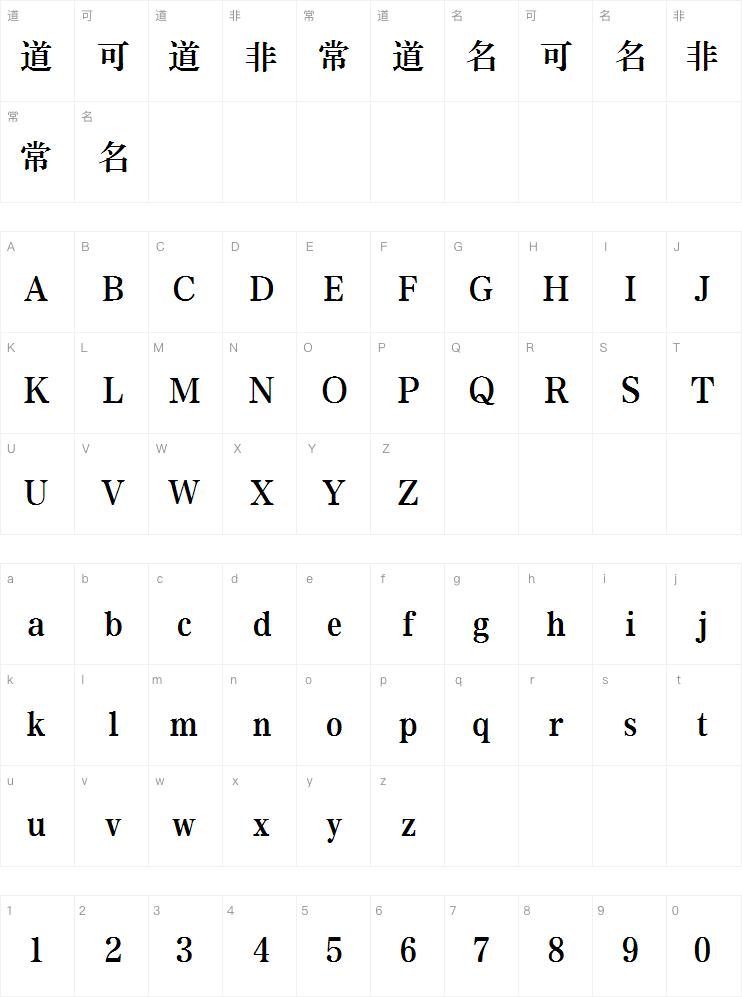
方正小标宋简
方正小标宋简体是一款标准宋体字体,由方正字库公司设计开发。它的特点是线条流畅,笔画清晰,整体感觉稳重大方,适合用于书籍、报纸、杂志等印刷品的排版。该字体的字形设计简单朴素,字体笔画粗细均匀,可读性强,是一款非常受设计师和企业品牌欢迎的中文字体,同时方正小标宋简体还具有非常良好的兼容性和可扩展性,可用于各种不同的印刷和数字媒体应用。